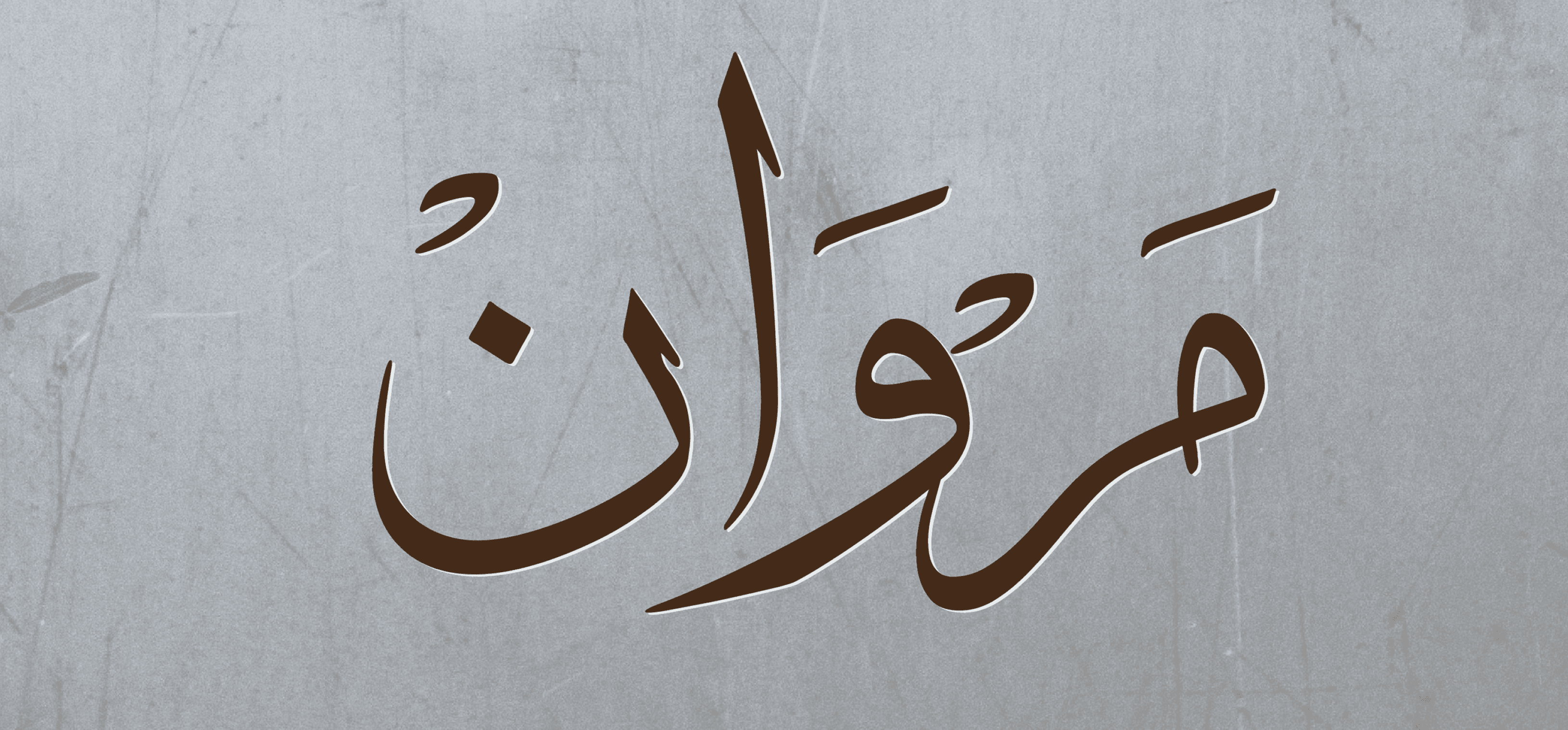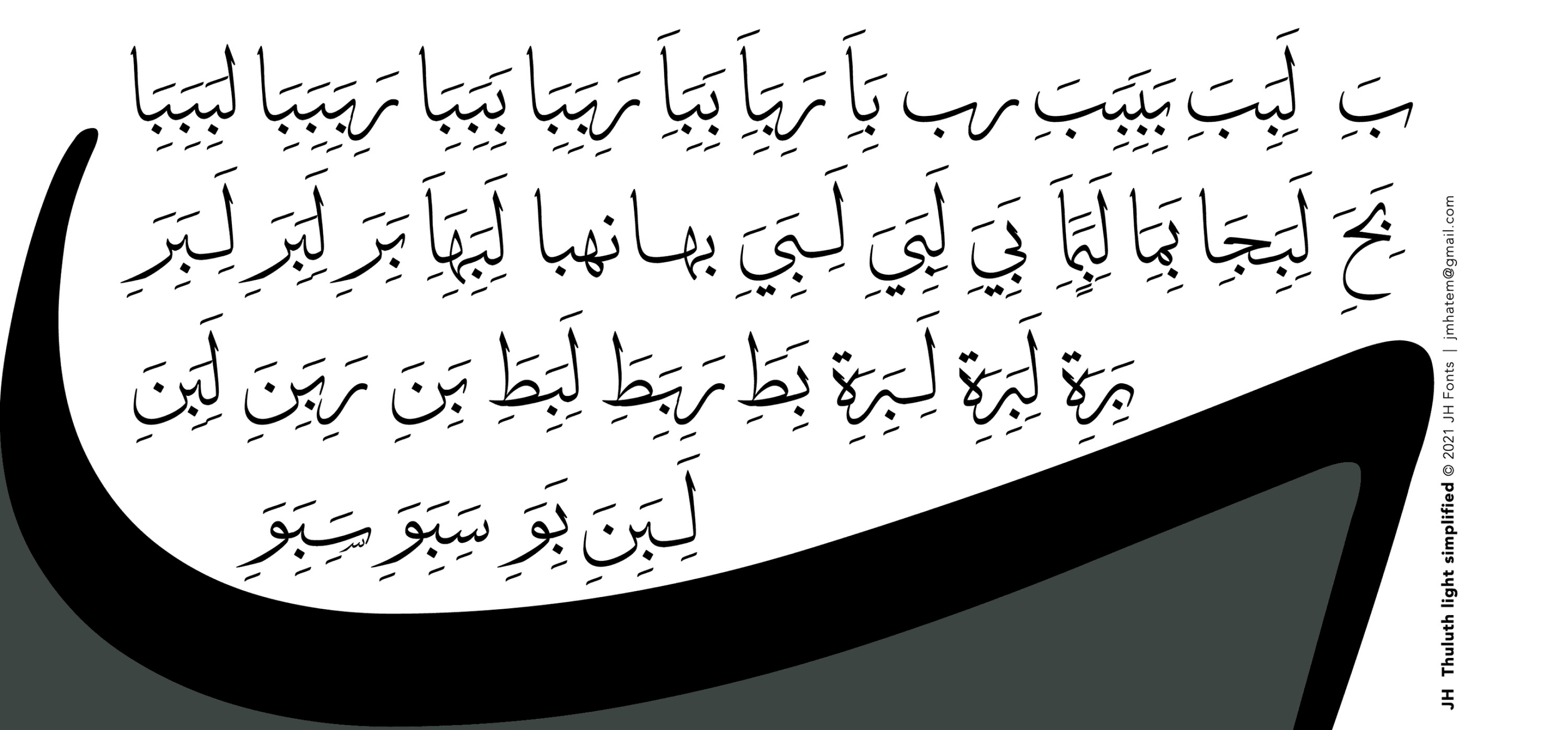
خط JH Haroun مستند إلى الخط الثلثي الكلاسيكي؛ ويضم أكثر من ألفي شكل (جليف) وامتدادات كاشيدة ذكية لمحاكاة الخط العربي الحقيقي. يُعد مثاليًا للعناوين، أغلفة الكتب، وبطاقات التهنئة.